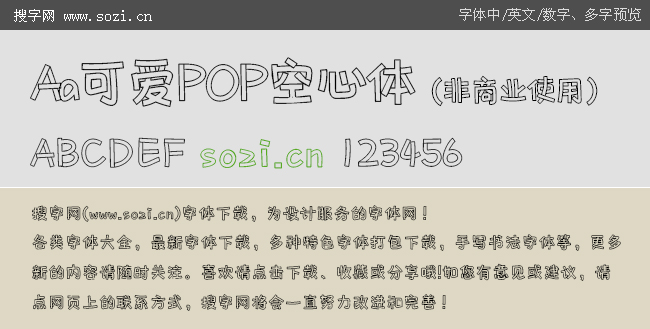
Aa可愛(ài)POP空心體
搜字網(wǎng)給大家提供一款A(yù)a可愛(ài)POP空心體(非商業(yè)使用)中文字體下載,Aa可愛(ài)POP空心體是一款卡通藝術(shù)字體,字形風(fēng)格活潑可愛(ài),手寫(xiě)的空心的筆畫(huà)又十分具有童趣。適合應(yīng)用于藝術(shù)設(shè)計(jì)、平面宣傳設(shè)計(jì)、網(wǎng)頁(yè)設(shè)計(jì)、海報(bào)設(shè)計(jì)等應(yīng)用(此字體為個(gè)人非商用版,商用可以聯(lián)系QQ:1006760504)。